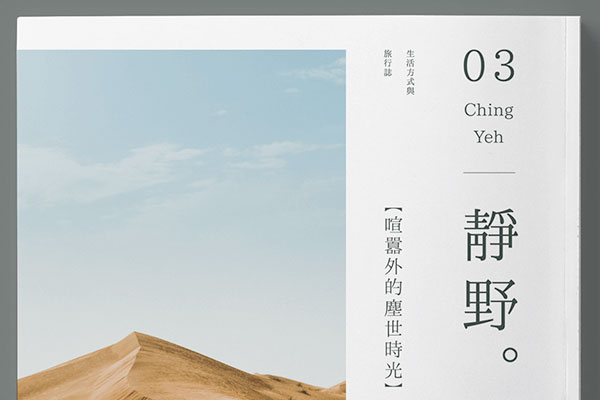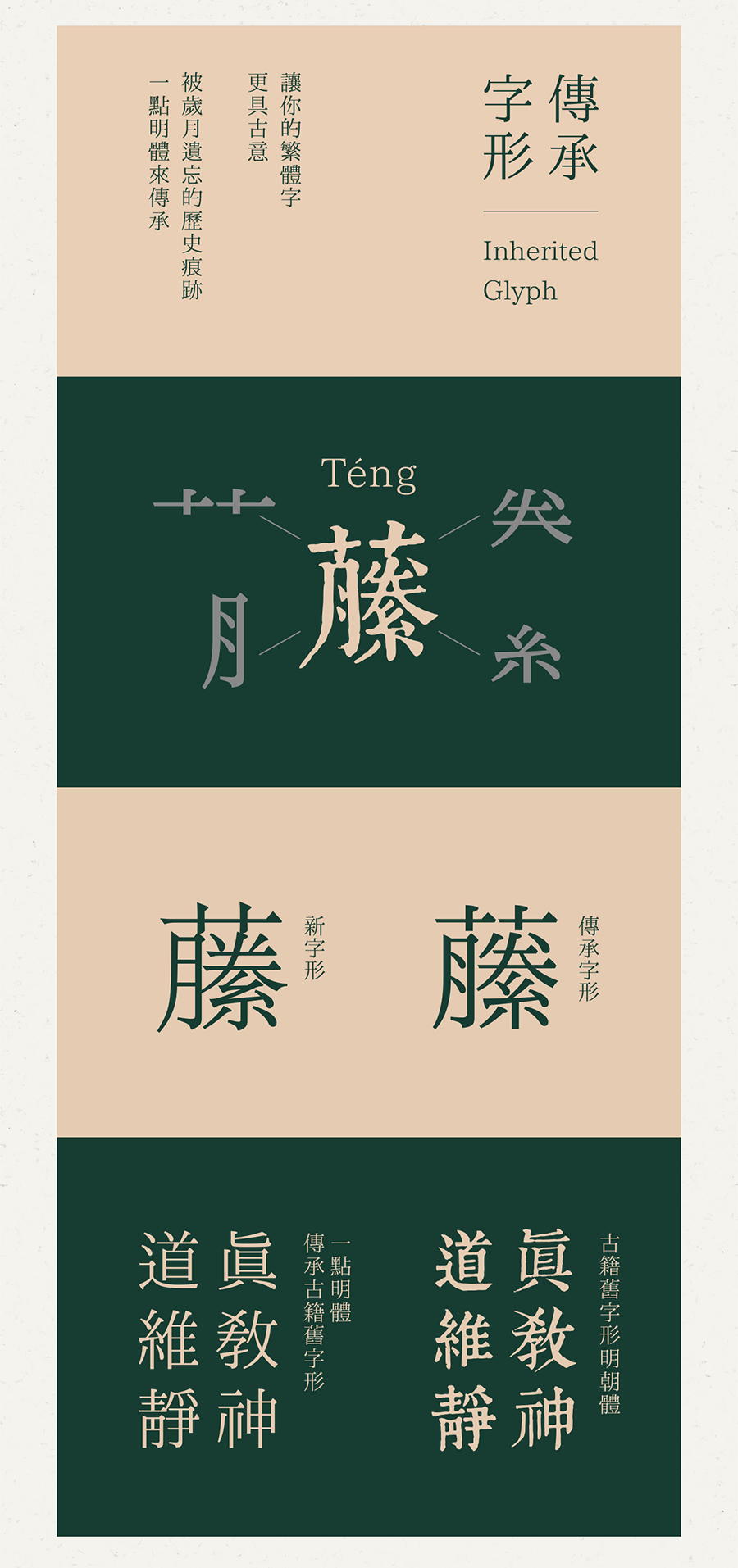
一点明体
2020.9.17更新记录:一点明体已于近期更新7.00版本,除了原来的正体(繁体)、日韩汉字、粤台闽客汉字等传承字形,以及注音符号、麻雀版、苏州码子,象棋等,也制作了旧字形的简化字,不会再碰到繁简不分的问题。无论正简日韩,都可以选择美观、平衡的传承字形!该字体对应的下载链接我们也已经更新至最新版!
一点明体(一點明體、I.Ming)的前身是刻石录明体,已由开源字型组织I.字坊(日本 一点字坊)全力维护。 明朝体在我们中国其实就是宋体,只是日本、韩国等国家才称为明体或明朝体。
一点明体依照传承字形标准化文件《传承字形部件检校表》的推荐字形标准制作,力求遵从字理,展现传承汉字构字的科学系统。同时,我们另备“一点明体异体”,呈现传统印版字中常见的异体。
目前一点明体已发布6.122版,发布日期为2020年4月13日。令人惊喜的是,该字体目前已囊括所有《现代汉语词典》中的常用简体3500字和台湾常用6763字。